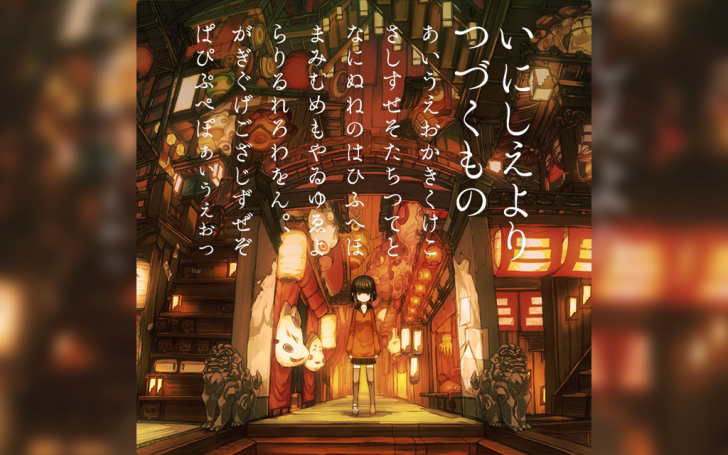
レトロな雰囲気の日本語フォント、40個を紹介します。
レトロなフォントを使うことで、デザインに味わいが生まれ、懐かしさ、暖かみ、親しみやすさを表現することができます。
無料で商用利用可能なものから、有料のものまで、和風で、昭和時代や明治時代っぽいレトロな日本語フォントです。
まにまに丸ゴチック
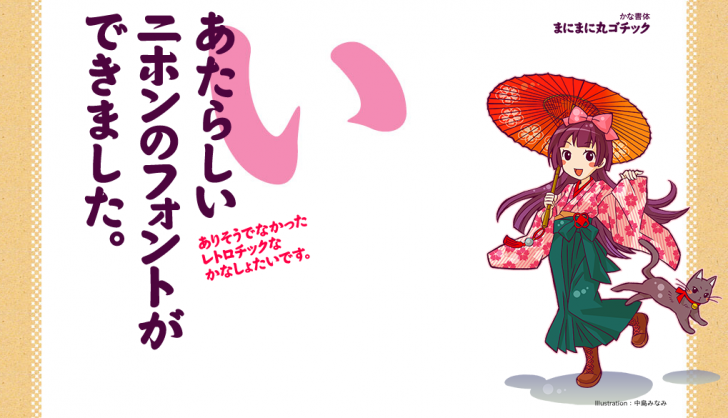
まにまに丸ゴチックは、ありそうでなかった、レトロチックな和風フォントです。太めのポップなデザインなのに、昭和レトロな雰囲気もある書体です。ひらがな、カタカナが収録されています。漢字や英数字は入っていないので、他のフォントと組み合わせて使います。お試し版「まにまにおためしばん!」は無料で利用できます。お試し版でも商用利用が可能です。製品版は今後、字種の拡張などが予定されています。
うずまさ本丸ゴシック
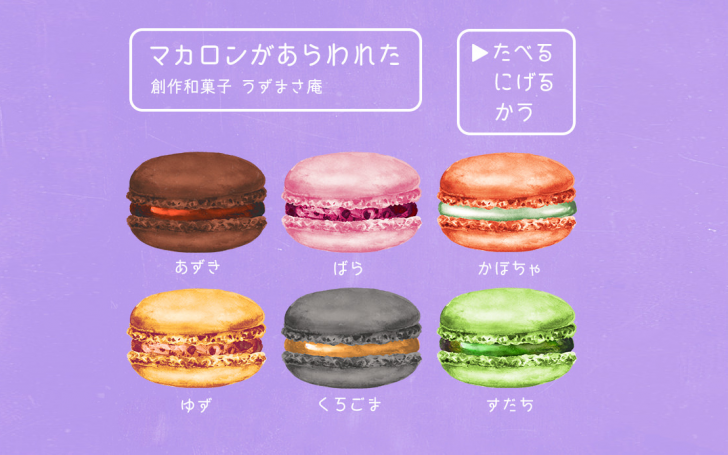
うずまさ本丸ゴシックは、京都を中心とした関西系の無声映画の字幕文字にインスピレーションを得た、味わいのある日本語フォントです。読みやすく、かわいい書体です。YouTubeの字幕や、Webのビジュアル、雑誌などの紙媒体まで、幅広く使うことができます。和風のデザインによく合います。無料ダウンロードできるうずまさ本丸ゴシックmini版と、商用利用可能な製品版があります。mini版にも漢字が収録されています。製品版は収録文字数が増えて、第二水準のよく使う漢字460字まで含まれます。また、無料版とは違い縦書きが可能です。
あさご本丸ゴシック
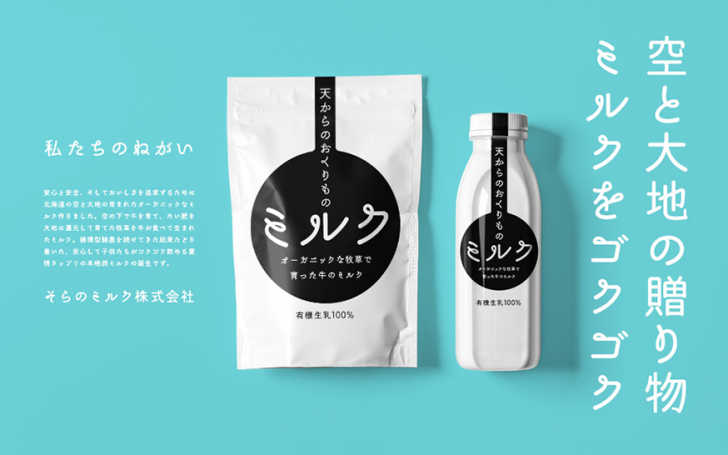
伝統的なイメージと、モダンさが両立した日本語ォントです。筆で流れるように書いた、クルクルとした線が特徴的な、遊び心にあふれたフォントです。美しい仕上がりのため、広告などのグラフィックデザインにもよく合います。無料でダウンロードできるあさご本丸ゴシックminiと、商用利用可能な製品版があります。mini版にも漢字が収録されています。製品版は収録文字数が増えており、クルクルとした線の形状が異なる6種類のフォントが追加収録されています。また、無料版とは違い縦書きが可能です。
いにしえよりつづくもの
いにしえよりつづくものは、明治時代にありそうな、筆で書いたような柔らかい印象のフォントです。同時に、現代的で洗練された仕上がりになっており、和風のデザインによく合います。ひらがなのみのフォントです。漢字やカタカナ、英数字は他のフォントと組み合わせて使います。
なつのおもいで
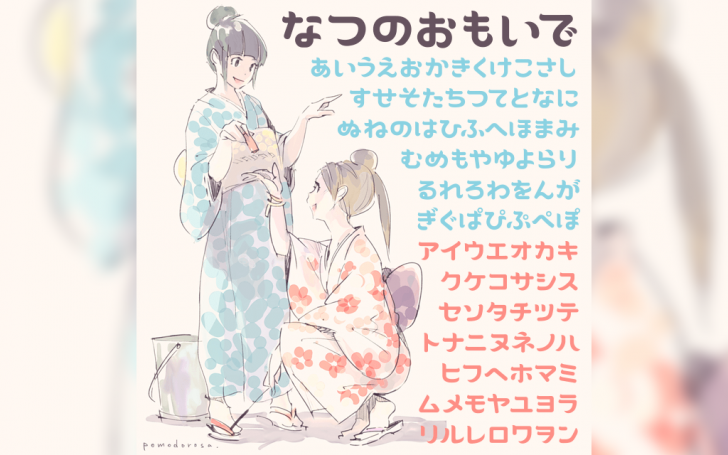
なつのおもいでは、ゆったりとした横幅の、日本を感じさせるフォントです。筆で書いたような流れのある動きと、現代的なデザインが特徴です。かわいらしい仕上がりになっています。ひらがな、カタカナのみのフォントです。漢字や英数字は他のフォントと組み合わせて使います。
おもてなし明朝
おもてなし明朝は、アンバランスな形が印象的な、和風レトロな雰囲気のフォントです。現代的なデザインにも合うようにデザインされており、見出しやロゴデザインへの使用にもおすすめです。シャープさと可愛らしさが両立した仕上がりです。ひらがな、カタカナのみのフォントです。漢字や英数字は他のフォントと組み合わせて使います。
おもてなし丸明朝
おもてなし丸明朝は、おもてなし明朝の角を丸くしたフォントです。和風レトロな雰囲気を残しつつ、よりかわいさが増しています。無料でダウンロードできます。商用利用はパッケージ版、ダウンロード版の購入が必要です。ひらがな、カタカナのみのフォントです。漢字や英数字は他のフォントと組み合わせて使います。
うつくし明朝体
うつくし明朝体は、商用利用可能な日本語のフリーフォントです。オールドスタイルの明朝体は、縦書きの美しい流れを重視してデザインされているので、横書きにすると文字組のバランスが崩れてしまうことがあります。このうつくし明朝体は、オールドスタイル明朝体の美しさを活かしつつ、横への流れを重視してデザインされており、横書きデザインでも美しさを損なうことなく使うことができます。漢字とかなは先端部分に丸みがあり、柔らかく、レトロな仕上がりです。漢字は第二水準まで収録れています。
かんじゅくゴシック
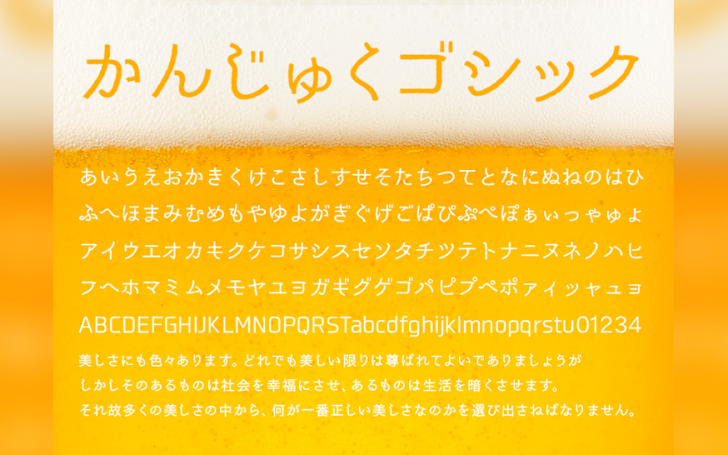
かんじゅくゴシックは、ガタガタとしたラインが深い味わいを醸している、少しレトロな雰囲気を持ったフォントです。バナーデザインなどに使用すると、味わい深い魅力的な仕上がりになります。無料ダウンロードできて、商用利用可能です。第二水準の漢字まで含まれています。
ショウワノニヲイ
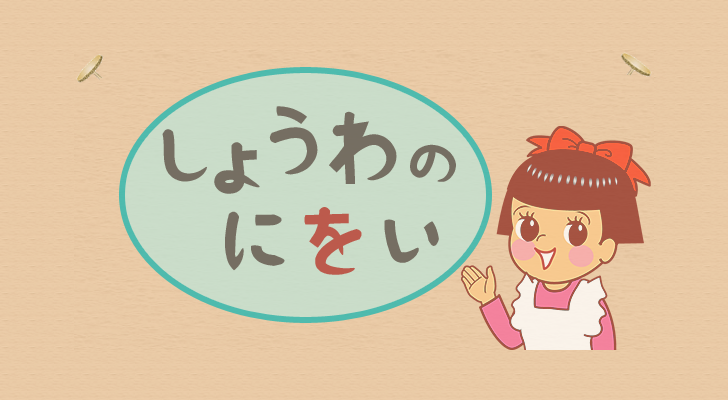
ショウワノニヲイは、その名の通り昭和レトロな雰囲気感を醸しだしている日本語フォントです。無料で商用利用できるフリーフォントです。
ほのかアンティーク丸
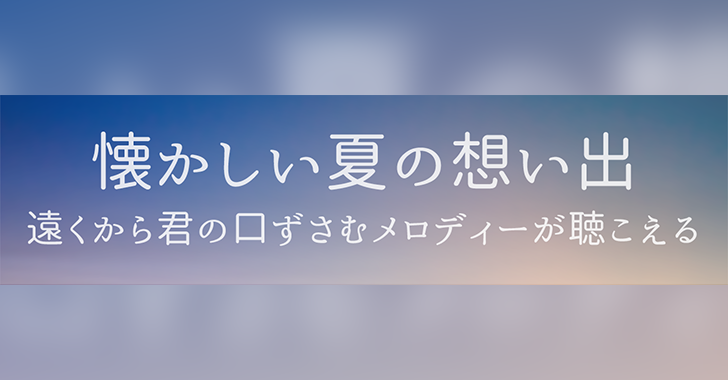
ほのかアンティーク丸は、明朝体風のかな文字と丸ゴシック系の漢字を組み合わせた、アンチック体の日本語フォントです。オールドスタイルで、哀愁の漂う、懐かしい雰囲気があります。一般的な日本語フォントに比べてかな文字が小さくデザインされた、和風な印象になっています。無料で商用利用が可能です。
ほのかアンティーク角
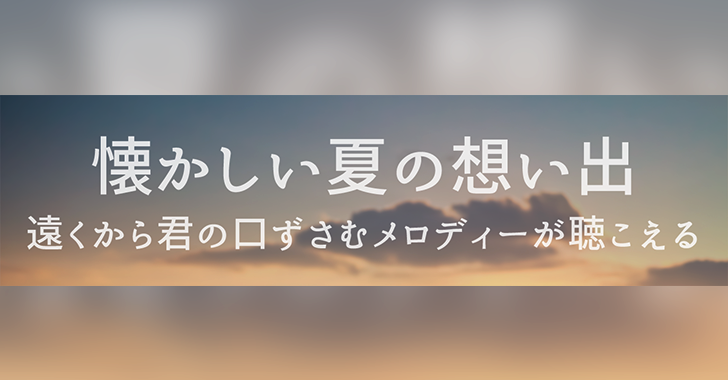
ほのかアンティーク角は、角ゴシックの漢字に、ウロコのついたかな文字を組み合わせたアンチック系(アンティーク体)のフォントです。ほのかアンティーク丸とは、またひと味違った楽しみ方ができます。商用利用可能なフリーフォントです。
こころ明朝体
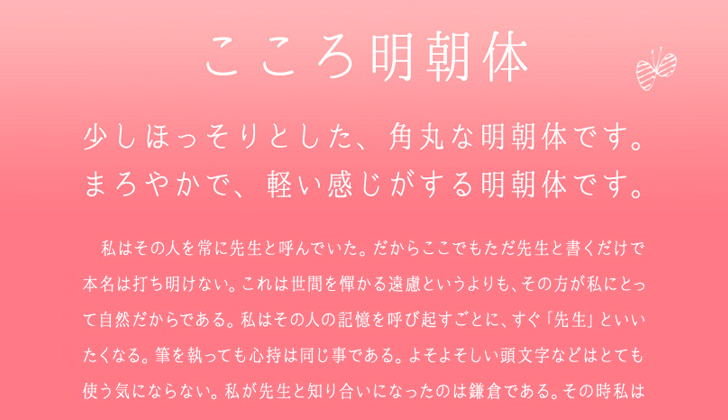
こころ明朝体は、細い字体の、柔らかく、軽やかな和風フォントです。夏目漱石の小説、「こころ」のような、こころが温まる書体です。無料で商用利用可能です。
はんなり明朝
はんなり明朝は、築地体にインスピレーションを得た、はんなりとしたスタイルの、まったりとしたレトロな和風フォントです。無料で商用利用可能です。
FGBゼロゴシック
FGBゼロゴシックは、人気のフリーフォントFGゼロをベースにリデザインされたフォントです。残念ながら、無料版のFGゼロは配布が終了しています。ゼロ戦の機体のプレートに使われていた文字にインスピレーションを得てデザインされており、シャープでレトロな印象が特徴的です。特にカタカナは一切の丸みがありません。漢字は第二水準まで収録されています。
FGPポテ丸レトロ
FGPポテ丸レトロは、フリーフォントとして配布されていたFGレトロが生まれ変わった有料フォントです。有料フォントなので、クライアントプロジェクトでも安心して使うことができます。FGPポテ丸レトロ、FGPポテガリレトロの2つの書体があります。FGPポテ丸レトロは、ぽってりとした、丸っこい文字が特徴です。レトロなデザインに仕上がっています。FGPポテガリレトロは、クレヨンで書いたようなガリガリとした丸い文字が特徴です。漢字は第二水準まで収録されています。
Cinecaption
Cinecaptionは、少し前の洋画の字幕で使われていたような懐かしい映画字幕風フォントです。商用でも無料で利用できるフリーフォントです。
シネマゴシックかな
シネマゴシックかなは、映画の字幕に使われている手書き風の文字を、ゴシック体にアレンジした、レトロ感のあるシネマフォントです。ひらがな、カタカナが入っています。ゴシック体の漢字と組み合わせて使います。太さの異なる7書体の有料フォントです。
レスラウンド
レスラウンドは、太めのデザインが特徴的なフォントです。安定感があり、昭和の遊園地のメリーゴーランドに使われていたような楽しい雰囲気のフォントです。個人利用のみ可能なフリーフォントです。
リトルビッグ
リトルビッグは、太いラインをベースとして、先端部分が豚のしっぽのように細くなっている、子豚のように愛嬌のあるフォントです。映画タイトルなどのデザインによく合います。個人利用のみ可能なフリーフォントです。